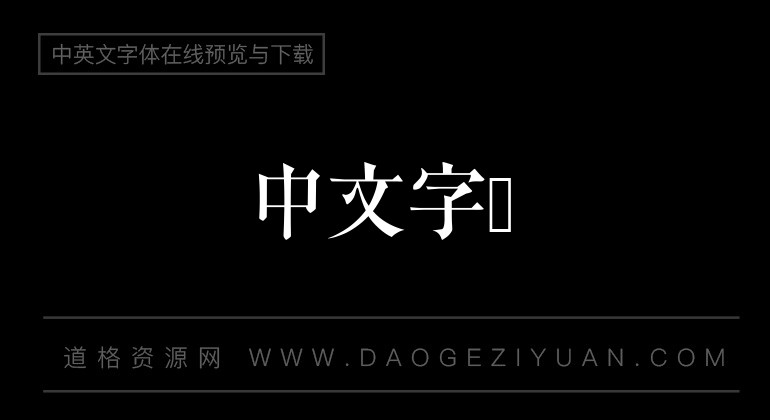
浙江民间书刻体
浙江民间书刻体是一种中国传统书法文化的独特表现形式,它来自浙江江南民间文化的传承,是浙江省文化的重要组成部分。浙江民间书刻体以宋体书法为基础,采用毛笔书法进行写作,具有浓重的民间色彩,在笔画的排列上也有较大的创新,形成了一种独特的书法风格。其特点是构图紧凑,折线流畅,笔画有力,结构严谨,笔画曲折,结构精练,表达简洁,构图精致,构图巧妙,色彩丰富,层次分明,给人以灵动、清新、细腻、淡雅的视觉感受。
浙江民间书刻体是一款非常不错的手写艺术字体,具有很好的视觉感,适合于文化类的宣传设计、商业类品牌的广告和产品包装设计以及个性化文字排版等较多场景。
浙江民间书刻体字符映射图